Креслярський шрифт та виконання написів на кресленнях
Кожен креслення супроводжується загальними, а також і додатковими пояснюють написами. ГОСТ 2.304-81 встановлює конфігурацію і розміри букв і цифр, що наносяться на всіх конструкторських документах.
Малюнок шрифту повинен бути ясним, чітким і красивим, без зайвих деталей, що ускладнюють сприйняття тексту.
При графічному оформленні ДП або КП рекомендується використовувати наступні типи шрифтів по ГОСТ 2.304-81:
· Тип А з нахилом близько 75 0 і без нахилу
· Тип Б з нахилом близько 75 0 і без нахилу
Накреслення літер українського алфавіту, цифр та знаків по ГОСТ 2.304-81 для шрифту типу Б з нахилом 75 0 показано на малюнку 14.
Малюнок 14 -Начертаніе букв українського алфавіту
На будівельних, топографічних кресленнях, схемах і графіках можна застосовувати спеціальні шрифти, наприклад, архітектурний вузький (як на малюнку 15), архітектурний романський, топографічний шрифт.
Крім зазначених вище шрифтів на плакатах застосовуються і інші шрифти. Наприклад, для заголовка і тексту, що пояснює значення умовних знаків і позначень, застосовують рубаний і брусковий шрифти.
На одному аркуші бажано використовувати шрифт одного малюнка.
· Для загальних заголовків - 25 ... ..30 мм
· Для заголовків графіків, діаграм, таблиць - 15 ... ..20 мм
· Для пояснювальних написів і позначень - 10 ... ..15 мм
Для цифр і букв на осях координат - 7 ... ..10 мм.
Малюнок 15 - Приклад написання букв архітектурним шрифтом
Встановлено такі розміри шрифтів, що визначаються висотою h (в мм) прописних літер: 2,5; 3,5; 5; 7; 10; 14; 20; 28; 40. Нахил букв і цифр у рядку - 75 # 730; .допускается найменування, заголовки, позначення до основного напису і на полі креслення писати без нахилу.
Таблиця 3 - Розміри букв та цифр українського алфавіту
Написи, що стосуються безпосередньо до зображення, можуть містити не більше двох рядків, що розташовуються над полицею лінії-виноски і під нею.
Текстову частину, поміщену на полі креслення, розташовують над основним написом.
Між текстовою частиною і основним написом не допускається поміщати зображення, таблиці і т.п.
На аркушах формату більш А4 допускається розміщення тексту в дві і більше колонки. Ширина колонки повинна бути не більше 185 мм.
На кресленні залишають місце для продовження сторінки змін.
На кресленні вироби, для якого стандартом встановлено таблиця параметрів (наприклад, зубчастого колеса, черв'яка і т.п.), її поміщають за правилами, встановленими відповідним стандартом. Всі інші таблиці розміщують на вільному місці поля креслення праворуч від зображення або нижче його і виконують згідно з ДСТУ 2.105 - 79.
Технічні вимоги на кресленні викладають, групуючи разом однорідні і близькі за своїм характером вимоги, по можливості в наступній послідовності:
а) вимоги, що пред'являються до матеріалу, заготівлі, термічній обробці і до властивостей матеріалу готової деталі (електричні, магнітні, діелектричні, твердість, вологість, гігроскопічність і т.д.), вказівка матеріалів-замінників;
б) розміри, граничні відхилення розмірів, форми і взаємного розташування поверхонь, маси і т. п .;
в) вимоги до якості поверхонь, вказівки про їх обробці, покритті;
г) зазори, розташування окремих елементів конструкції;
д) вимоги, що пред'являються до налаштування і регулювання вироби;
е) інші вимоги до якості виробів, наприклад: безшумність, вібростійкість, самоторможіння і т. д .;
ж) умови і методи випробувань;
з) вказівку про маркування і таврування;
і) правила транспортування та зберігання;
к) особливі умови експлуатації;
л) посилання на інші документи, що містять технічні вимоги, що поширюються на даний виріб, але не наведені на кресленні.
Пункти технічних вимог повинні мати наскрізну нумерацію. Кожен пункт технічних вимог записують з нового рядка.
Тема «Технічні вимоги» не пишуть.
У разі якщо необхідно вказати технічну характеристику виробу, її розміщують окремо від технічних вимог, з самостійної нумерацією пунктів, на вільному полі креслення під заголовком «Технічна характеристика». При цьому над технічними вимогами поміщають заголовок «Технічні вимоги». Обидва заголовка не підкреслює.
Для визначення величини зображеного вироби і його елементів служать розмірні числа, нанесені на кресленні.
Необхідна точність вироби при виготовленні задається зазначенням на кресленні граничних відхилення розмірів, а також граничних відхилень форми і розташування поверхонь.
Загальна кількість розмірів на кресленні повинна бути мінімальною, але достатньою для виготовлення і контролю вироби.
Довідкові розміри на кресленні позначають знаком «*», а в технічних вимогах записують: «* Розміри для довідок». Якщо все розміри на кресленні довідкові, їх знаком "*" не відзначають, а в технічних вимогах записують: «Розміри для довідок».
На кресленнях виробів у розмірів, контроль яких технічно утруднений; наносять знак «*», а в технічних вимогах поміщають напис «Розміри обеспеч. інстр. ». Зазначена напис означає, що виконання заданого кресленням розміру з граничним відхиленням повинно гарантуватися розміром інструменту або відповідним технологічним процесом.
Не допускається повторювати розміри одного і того ж елемента на різних зображеннях, в технічних вимогах, основного напису і специфікації. Виняток становлять довідкові розміри (перенесені з креслень виробів-заготовок, розміри деталей (елементів) з сортового, фасонного, листового і др.проката).
Лінійні розміри і їх бокові відхилення на кресленнях і в специфікаціях вказують в міліметрах, без позначення одиниці виміру. Якщо на кресленні розміри необхідно вказати не в міліметрах, а в інших одиницях виміру (сантиметрах, метрах і т.д.), то відповідні розмірні числа записують з позначенням одиниці виміру (см, м) або вказують їх в технічних вимогах.
Для розмірів і граничних відхилень, наведені у технічних вимогах і пояснювальних написах на полі креслення, обов'язково вказують одиниці виміру.
При розташуванні елементів предмета (отворів, пазів, зубів і т. П.) На одній осі або на одному колі розміри, що визначають їх взаємне розташування, наносять у такий спосіб:
- від загальної бази (поверхні, осі);
- завданням розмірів декількох груп елементів від декількох загальних баз - малюнок 16;
- завданням розмірів між суміжними елементами (ланцюжком) - малюнок 17.
Розміри на кресленнях не допускається наносити у вигляді замкненого кола, за винятком випадків, коли один з розмірів зазначений як довідковий.
Розміри, що визначають положення симетрично розташованих поверхонь у симетричних виробів, наносять, як показано на малюнках 18 і 19.
Для всіх розмірів, нанесених на робочих кресленнях, вказують граничні відхилення.
Допускається не вказувати граничні відхилення:
а) для розмірів, що визначають зони різної шорсткості однієї і тієї ж поверхні, зони термообробки, покриття, обробки, накатки, насічки, а також діаметри торованих і насічених поверхонь. У цих випадках безпосередньо у таких розмірів наносять знак ≈;
б) для розмірів деталей виробів одиничного виробництва задаються з припуском на пригін.
При нанесенні розміру прямолінійного відрізка розмірну лінію проводять паралельно цьому відрізку, а виносні лінії - перпендикулярно розмірами малюнок 20.
При нанесенні розмірів потрібно пам'ятати, що на всіх кресленнях не залежно від масштабу вказуються дійсні розміри вироби.
Розмірні числа в межах одного креслення виконують шрифтом одного розміру. Розмірні числа наносять над розмірною лінією якомога ближче до її середини. При нанесенні декількох паралельних або концентричних розмірних ліній на невеликій відстані один від одного розмірні числа над ними рекомендується розташовувати в шаховому порядку малюнок 21. При нанесенні розміру діаметра всередині кола розмірні числа зміщують щодо середини розмірних ліній.
Розмірні числа лінійних розмірів при різних нахилах розмірних ліній мають у своєму розпорядженні, як показано на малюнку 22.
Якщо необхідно нанести розмір в заштрихованої зоні, відповідне розмірне число наносять на полиці лінії-виноски.
Стрілки, що обмежують розмірні лінії повинні упиратися вістрям у відповідні лінії контуру, або виносні, або осьові лінії.
Виносні лінії повинні виходити за кінці розмірних стрілок на 1. 5 мм малюнок 23.
Мінімальна відстань між паралельними розмірними лініями повинно бути 7 мм, а між розмірною і лінією контуру - 10 мм і обрані в залежності від розмірів зображення і насиченості креслення.
Необхідно уникати перетину розмірних і виносних ліній.
Не допускається використовувати лінії контуру, осьові, центрові і виносні лінії в якості розмірних.
Допускається проводити розмірні лінії безпосередньо до ліній видимого контуру, осьових, центровим і інших лініях.
Виносні лінії проводять від лінії видимого контуру, за винятком випадків, коли при нанесенні розмірів на невидимому контурі відпадає необхідність в кресленні додаткового зображення.
Якщо вид чи форму симетричного предмета або окремих симетрично розташованих елементів зображують тільки до осі симетрії або з обривом, то розмірні лінії, що відносяться до цих елементів, проводять з обривом, і обрив розмірної лінії роблять далі осі чи лінії обриву предмета малюнок 25.
Розмірні лінії допускається проводити з обривом в наступних випадках:
а) при вказуванні розміру діаметра окружності незалежно від того, зображена чи окружність повністю або частково, при цьому обрив розмірної лінії роблять далі центра кола малюнок 24;
б) при нанесенні розмірів від бази, що не зображеної на даному кресленні малюнок 25.
При зображення вироби з розривом розмірну лінію не переривають малюнок 26.
Якщо довжина розмірної лінії недостатня для розміщення на ній стрілок, то розмірну лінію продовжують виносити за виносні лінії (або відповідно за контурні, осьові, центрові і т. Д.) І стрілки наносять, як показано на малюнку 27.
При нестачі місця для стрілок на розмірних лініях, розташованих ланцюжком, стрілки допускається замінити зарубками, що наносяться під кутом 45 ° до розмірних лініях або чітко наносяться точками.
При нестачі місця для стрілки через близько розташованої контурної або виносної лінії останні допускається переривати.
Якщо для написання розмірного числа недостатньо місця над розмірною лінією, то розміри наносять, як показано на малюнку 25; якщо недостатньо місця для нанесення стрілок, то їх наносять, як показано на малюнку 26.
Спосіб нанесення розмірного числа при різних положеннях розмірних ліній (стрілок) на кресленні визначається найбільшим зручністю читання.
Розмірні числа і граничні відхилення, не допускається розділяти або перетинати якими б то не було лініями креслення.
Не допускається розривати лінію контуру для нанесення розмірного числа та наносити розмірні числа в місцях перетину розмірних, осьових або центрових ліній.
У місці нанесення розмірного числа осьові, центрові лінії та лінії штрихування переривають малюнок 29.
Розміри двох симетрично розташованих елементів виробу (крім отворів) наносять один раз без зазначення їх кількості, групуючи, як правило, в одному місці все розміри малюнок 30 і 31. Кількість однакових отворів завжди вказують повністю, а їх розміри - тільки один раз.
Розміри на будівельних кресленнях наносять відповідно до ГОСТ 2.307- 68 * з урахуванням вимог ГОСТ 21.101- 97.
Розміри в міліметрах на будівельних кресленнях, як правило, наносять у вигляді замкнутого ланцюжка без вказівки одиниці виміру. Якщо розміри проставляють в інших одиницях, це обговорюють в примітці до креслень. Розмірні лінії на будівельних кресленнях обмежують зарубками - короткими штрихами довжиною 2 4 мм, проведеними з нахилом вправо під кутом 45º до розмірної лінії. Товщина лінії зарубки дорівнює товщині суцільної основної лінії, прийнятої на даному кресленні. Розмірні лінії повинні виступати за крайні виносні лінії на 1-3мм. Розмірне число розташовують над розмірною лінією приблизно на відстані 1 мм. Виносна лінія повинна виступати за розмірну на 1-5мм. При нестачі місця для зарубок на розмірних лініях, які представляють собою замкнутий ланцюжок, зарубки допускається замінювати точками, відповідно до малюнком 32.
Відстань від контуру креслення до першої розмірної лінії рекомендується приймати не менше 10 мм. Однак на практиці це відстань приймають рівним 15 ... 20 мм. Відстань між паралельними розмірними
лініями повинно бути не менше 7 мм, а від розмірної лінії до маркувального
гуртка координаційної осі - 4 мм. Гуртки для позначення координаційних осей приймають діаметром 6 ... .12 мм, відповідно до малюнком 33.
На першій розмірної лінії (ланцюжку) проставляють розміри простінків і прорізів. На другий ланцюжку вказують відстань між сусідніми координаційними осями. На третій розмірної ланцюжку вказують відстань між крайніми координаційними осями. Розміри прив'язки зовнішніх стін до координаційних осей проставляють перед першою розмірної ланцюжком, як показано на малюнку 33.
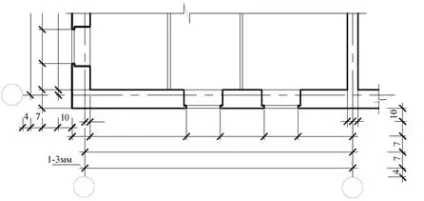
При наявності в зображенні ряду однакових елементів, розташованих на рівних відстанях один від одного (наприклад, осей колон), розміри між ними проставляють тільки на початку і в кінці ряду, малюнок 34, і вказують сумарний розмір між крайніми елементами у вигляді твору числа повторень на повторюваний розмір.
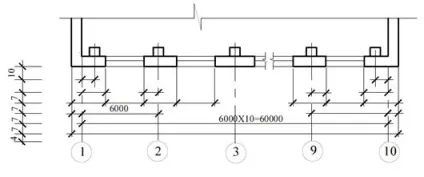
Висотні позначки. Відповідно до ГОСТ 21.105-79 позначки рівнів (висоти, глибини) на планах, розрізах, фасадах показують відстань по висоті від рівня чистої підлоги першого поверху до рівня поверхні різних елементів будівлі. У цьому випадку рівень чистого статі першого поверху приймають за відліковий рівень - умовної «нульовий» позначки.
На розрізах і фасадах позначки поміщають на виносних лініях або лініях контуру. Знак позначки рівня являє собою стрілку у вигляді прямого кута, який вершиною спирається на виносну лінію, з короткими
(2 ... .4 мм) сторонами, проведеними основними лініями під кутом 45 ○ до виносної лінії рівня відповідної поверхні. Вертикальний відрізок і горизонтальну полицю знака виконують суцільними тонкими лініями. Розмір вертикального відрізка рекомендується приймати від 4 до 6 мм в залежності від розмірів креслення. Довжина горизонтальної полички може бути
прийнята від 11 до 15 мм, рисунок 35. При необхідності розмір вертикального відрізка і довжину горизонтальної полички можна збільшити.
Якщо близько одного зображення кілька знаків рівнів розташовуються один
над одним, то вертикальні лінії висотних відміток рекомендується розміщувати на одній вертикальній прямій, а довжину горизонтальних поличок робити однаковими, малюнок 35. Висотні позначки вказують в метрах з трьома десятковими знаками після коми. Умовну нульову позначку позначають «0.000» без знака, відповідно до малюнком 35. Відмітки нижче умовної нульової позначають зі знаком мінус (-), позначки вище умовної нульової - зі знаком плюс (+). Як нульової позначки для будівель приймають, як правило, рівень підлоги першого поверху.
Відмітки при необхідності супроводжуються пояснювальними написами, наприклад Ур.ч.п.- рівень чистого статі. Ур.з.- рівень землі, малюнок 36.